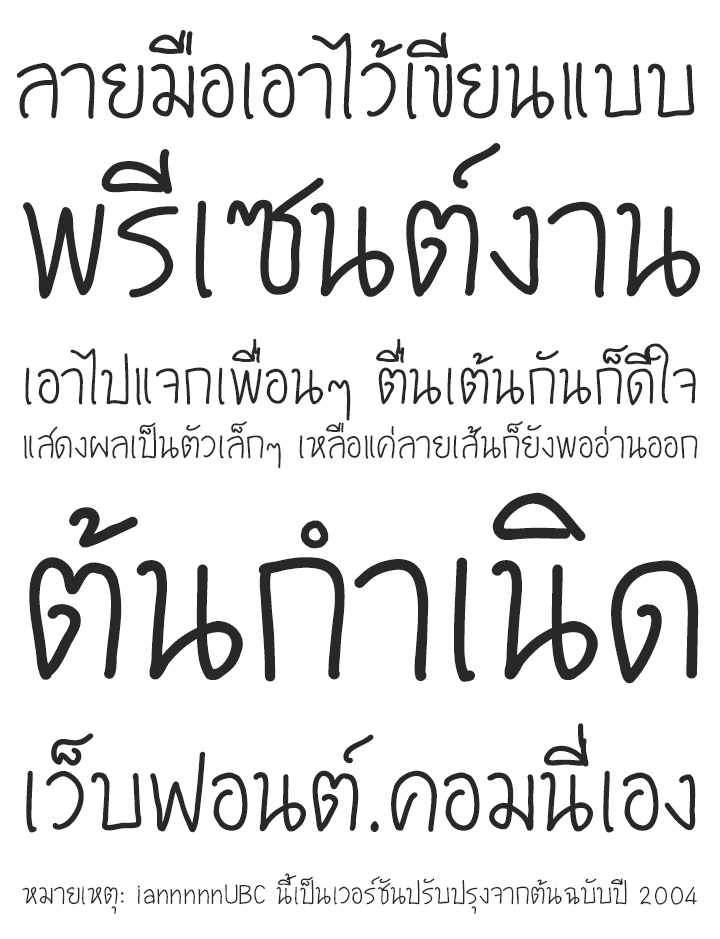
ฟอนต์ตัวแรกในชีวิตของผม หัดทำตอนจะส่งวิทยานิพนธ์เพียงเพราะอยากได้ฟอนต์ที่เป็นลายมือตัวเองไว้บรรยายภาพส่งอาจารย์ โดยไม่มีความรู้เรื่องการทำฟอนต์เลย พอเสร็จแล้วสนุกดี ก็เลยแรงบันดาลใจที่จะทำฟอนต์อีกเยอะๆ จนเกิดเป็นเว็บฟอนต์.ไอ้แอนนนนน และ ฟอนต์.คอมในที่สุด!
หมายเหตุ: ฟอนต์ iannnnnUBC ตัวนี้เป็นเวอร์ชันปรับปรุงจาก 2004_iannnnnUBC ที่ทำมาก่อนหน้า และถูกแก้ไขขัดเกลาเป็นเวอร์ชัน 2005 ในปัจจุบัน
iannnnnUBC